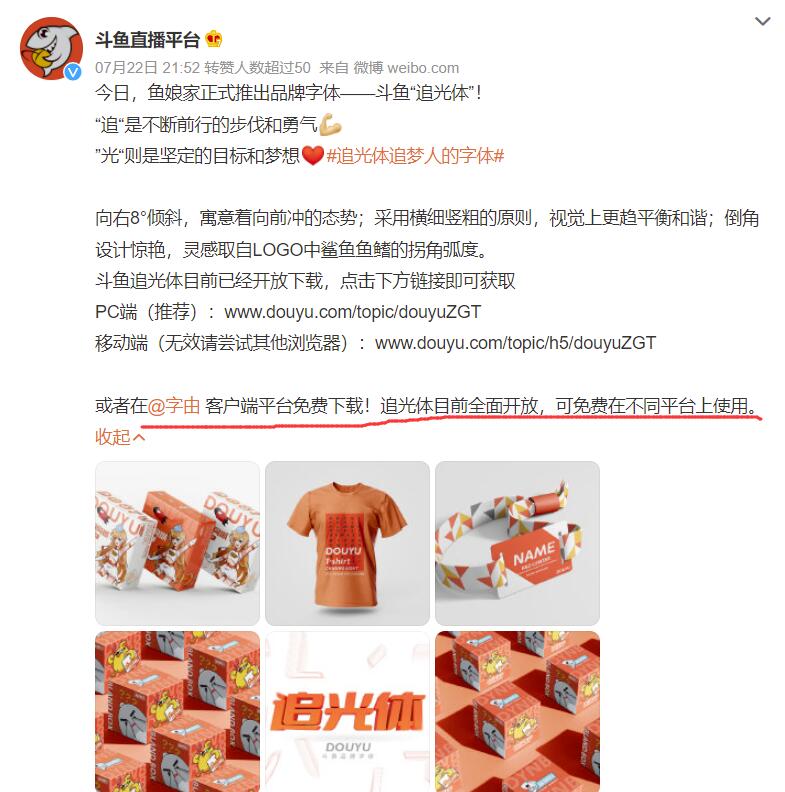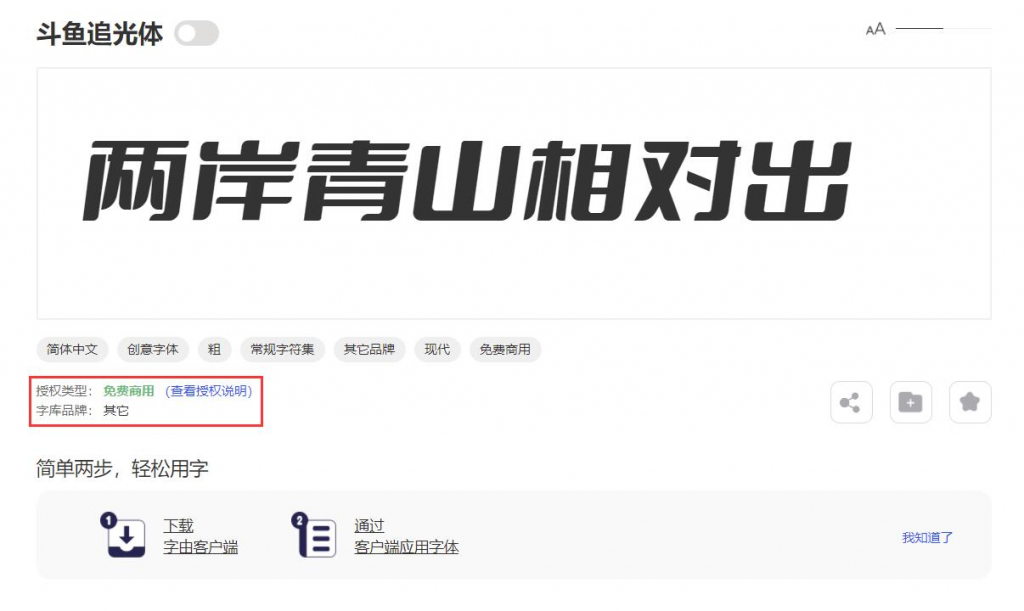
斗鱼追光体:以梦为马追光而行 斗鱼首款免费商用字体发布
斗鱼追光体,是由斗鱼武汉研发部UED提供指导,品牌组设计成员主导设计的全新品牌字体。很多人会问,斗鱼为什么要设计自己的字库,我们并非心血来潮,作为一个在国内知名的直播平台公司,我们需要统一的字体来发声,来表现企业自身的风格,并且向外界传递我们自己的品牌特质。我们也想统一公司内所有的子品牌标志与各项目的宣传形象,在视觉上用同一种声音来凸显斗鱼。我们希望用户想到斗鱼公司时,是会联想到一个具有活力、上进,且具有娱乐性质的科技型公司。我们设计团队也是秉承着这些,来设计这套字体。
斗鱼追光体是符合GB2312简体中文编码字符标准的专属品牌字体。是拥有一种标准版字重,包含6763个中文字符,100个西文及数字符号。随着斗鱼品牌场景的日益丰富,斗鱼追光体能逐渐适配平台的各种场景。
斗鱼追光体 2.0: 输入美元符号 $,显示的是 人民币符号¥。做外贸价格标识牌的朋友,千万不要忘了仔细对稿啊!
在斗鱼追光体2.0中,对拉丁文进行补充与扩展;新增日文平假名、片假名;新增台湾地区所使用的汉语注音符号;新增货币符号、字母式符号、罗马数字、上标和小标等;
• 已更新2.0。字体设计值得夸赞,不过制作技术仍旧太差,字符单位零乱不统一、字形轮廓及方向错误、中英文大小不协调、符号问题、横竖排问题、命名问题、il1问题等等一大堆。改好花了大半天。。。
斗鱼追光体 v1.00缺陷:WPS 中,如果大段文字使用此字体,英文/阿拉伯数字的字距显示正常。
但中文左右严重叠字,两个中文字之间,需要填充2个英文空格,才能正常显示中文。建议后续版本优化。
质量真的很高了!!!
很漂亮的一套标题体,赞
缺点就是分不清I、l、1。